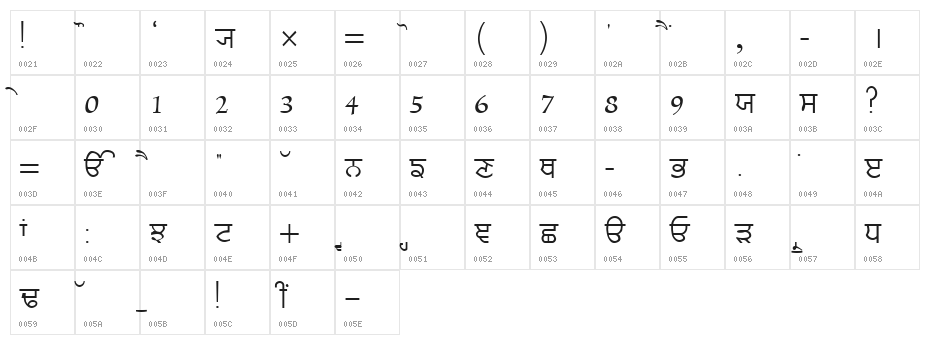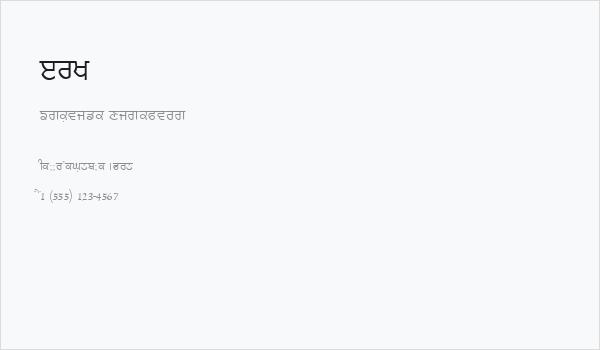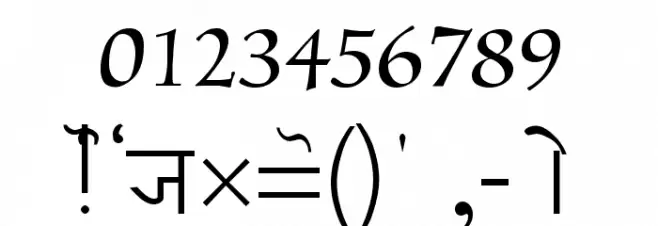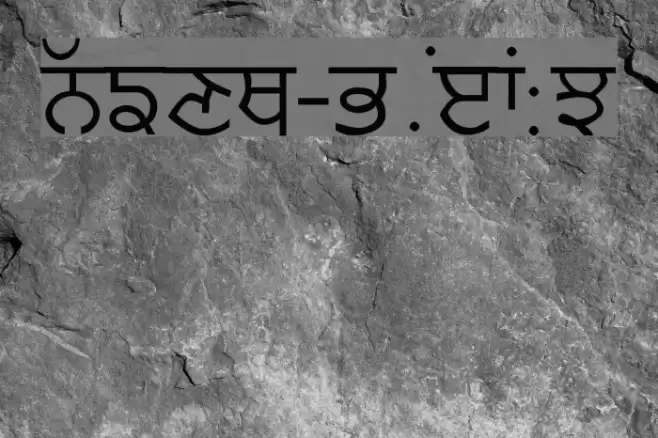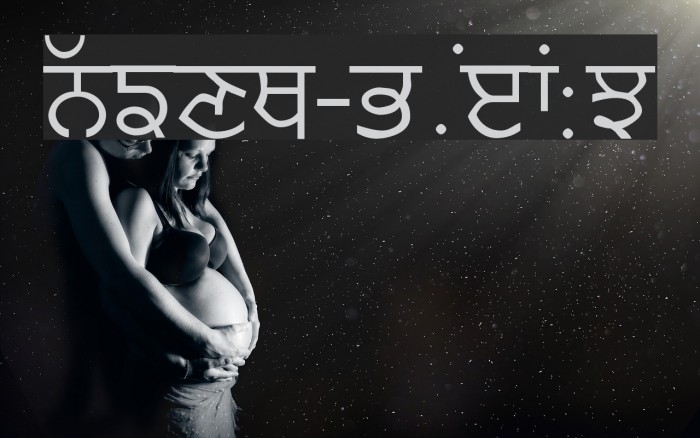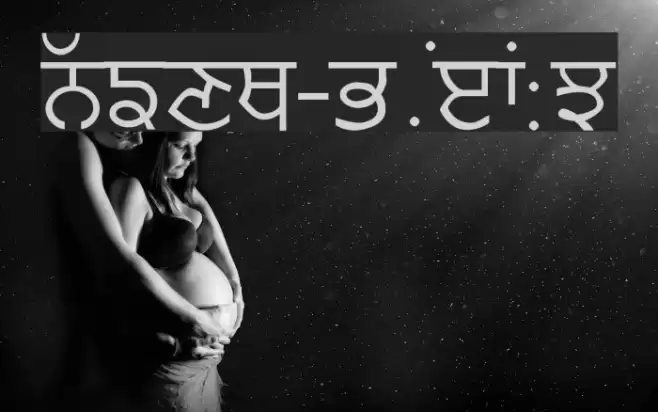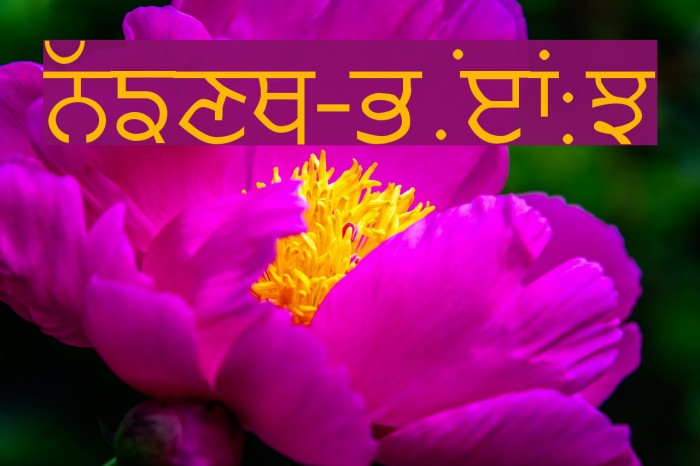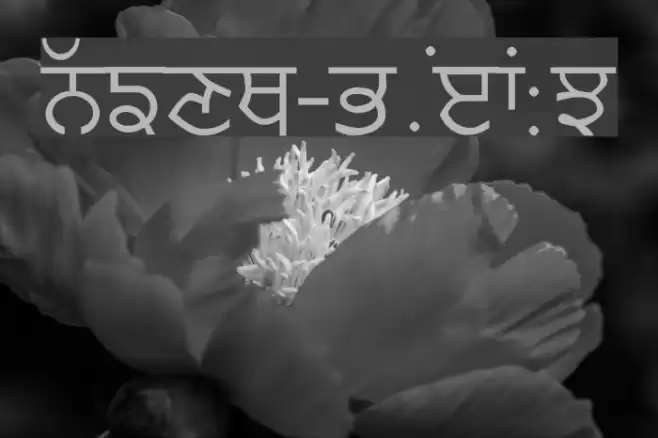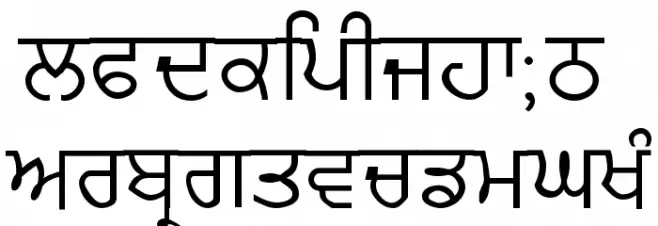
Joy Font
| Nombre | Joy |
| Peso | Normal |
| Categorías | Asian |
| Caso de uso | Headlines, Body text, Logos |
| Proyectos propuestos | This font is perfect for use in educational materials, signage, and digital interfaces where clarity is paramount. It can also be used in branding projects that require a modern yet timeless appeal. |